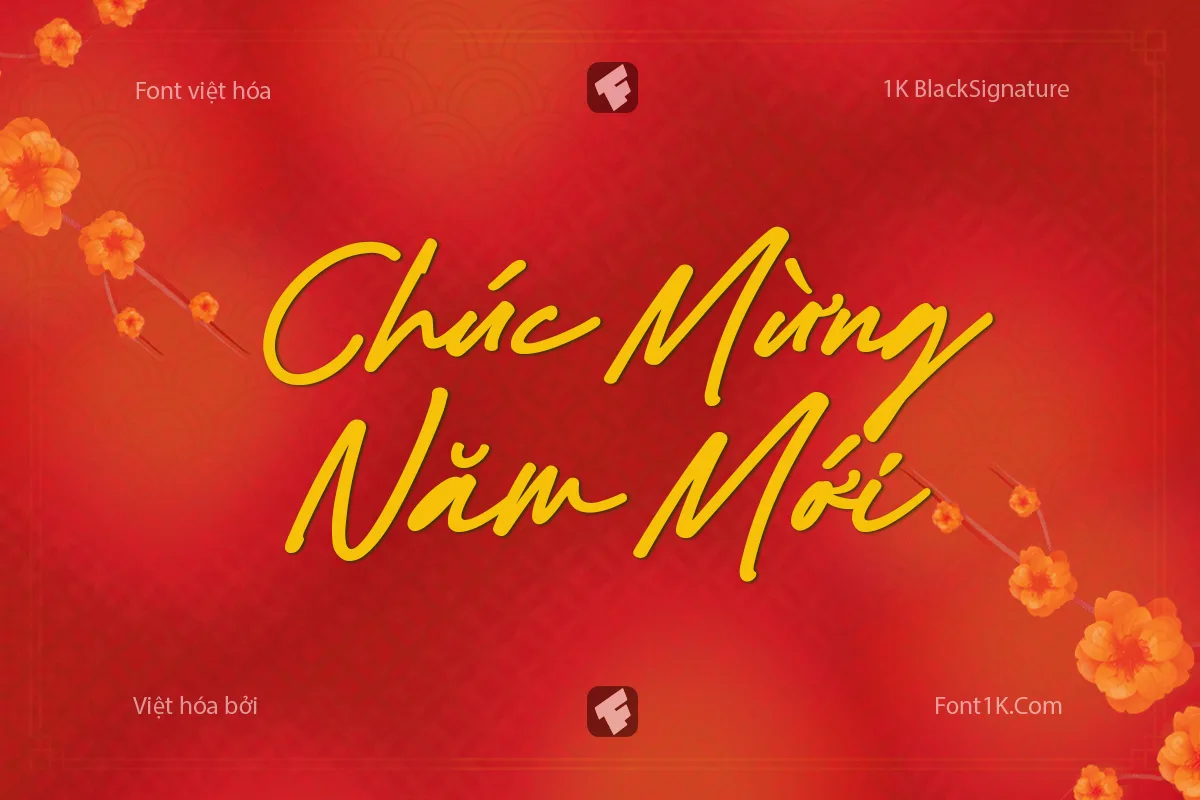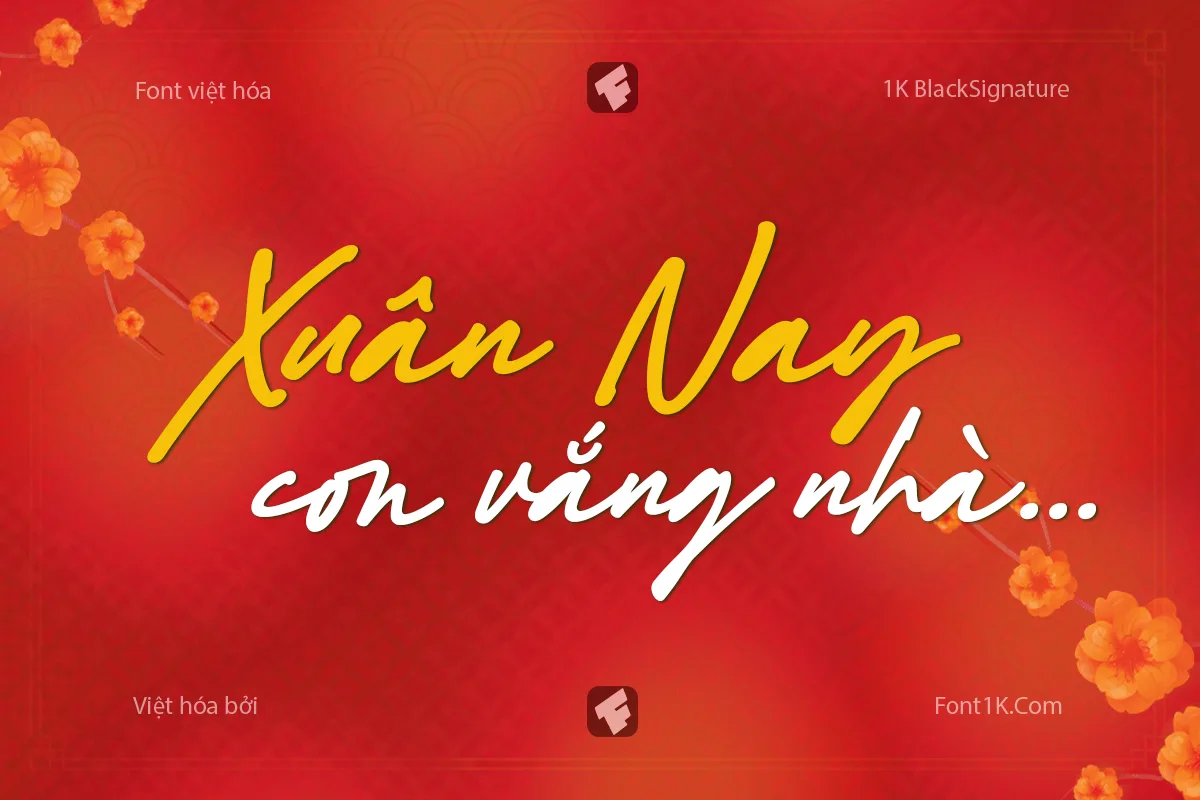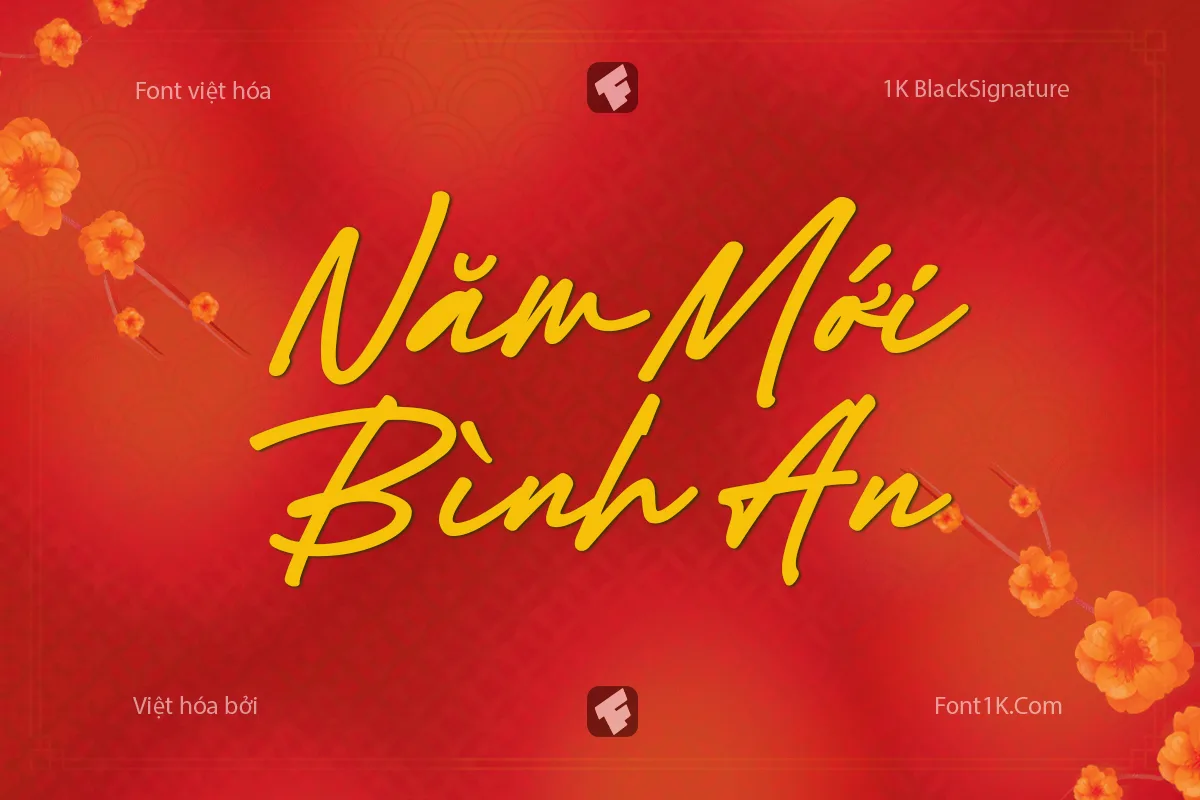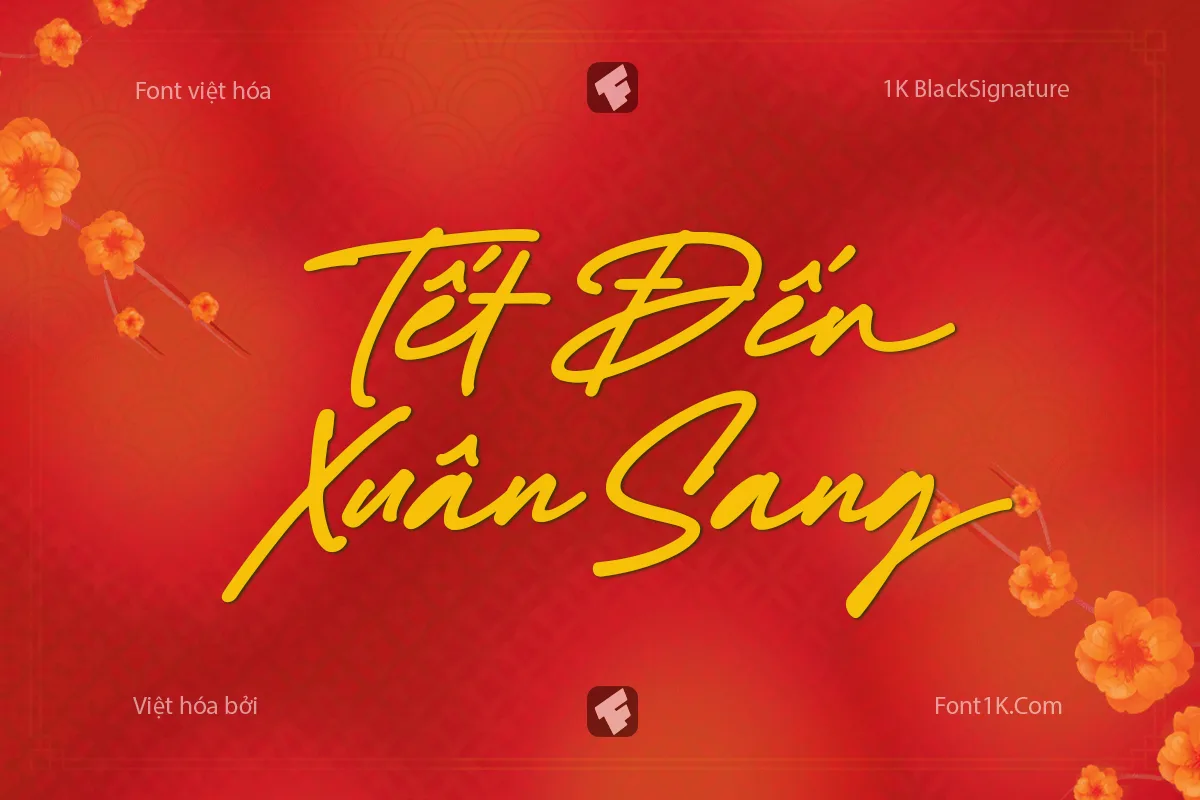
1K Black Signature là phông chữ viết tay đẹp có nhiều ký tự thay thế, ký tự theo ngữ cảnh (liga) giúp bạn thuận tiện hơn trong thiết kế. Bộ font này có thể làm tiêu đề chính, chữ ký hoặc thiết kế các chủ đề cần tính chất sáng tạo.
Giới thiệu Font việt hóa 1K Black Signature
1K Black Signature là một font chữ viết tay (font chữ ký) đẹp được thiết kế bởi Mans Greback, bản thân nó đã có tiếng Việt tuy nhiên vẫn còn dính dấu một số chữ cái, phiên bản Việt hóa bởi Font1K đã được fix triệt để các lỗi dính dấu và kerning lại phần tiếng Việt.
Đặc điểm nổi bật của font chữ 1K Black Signature
Font chữ 1K Black Signature mang phong cách viết tay nên có thể ứng dụng vào rất nhiều chủ đề thiết kế khác nhau. Sau đây là các đặc điểm đáng chú ý của font chữ Black Signature.
- 1K Black Signature được thiết kế theo phong cách chữ ký, nó có nhiều ký tự thay thế và các ký tự theo ngữ cảnh bao gồm cả tiếng Việt.
- 1K Black Signature được Font1K Việt hóa lại một số ký tự và dấu mới nhằm tránh dính dấu các ký tự như T, t, R, L …
- 1K Black Signature các ký tự theo ngữ cảnh được kích hoạt sẵn theo code Standard Ligatures, Discretionary Ligatures giúp bạn dễ sử dụng hơn với các phần mềm thiết kế đặc biệt các phần mềm trên điện thoại.
Hình ảnh demo font việt hóa 1K Black Signature